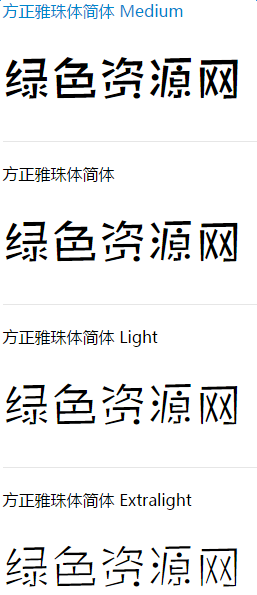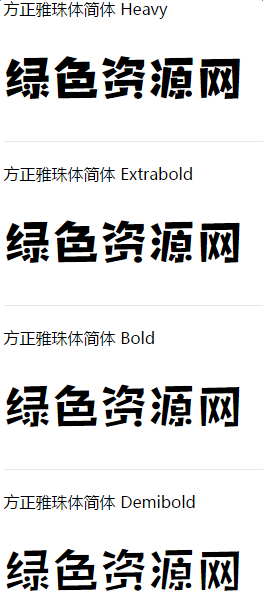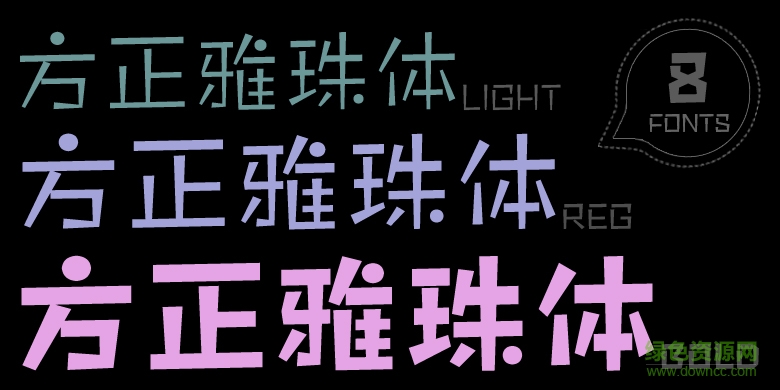
方正雅珠体是方正出品的字体,该字体粗细相间,钢劲有力,变化得当,深受广大文字书法爱好者喜欢,欢迎大家来本站踊跃下载哦!
方正雅珠体打破了传统字体的笔形和结构,将笔画以图形化的手法进行处理,且富于变化,横画处理成粗壮的矩形,竖划则近似于倒梯形,点、撇、捺、提也都处理成不规则的梯形,部分点画处理成椭圆形,整体给人以稚拙、欢快、跳脱、无拘无束、充满童趣的感觉,非常适合儿童相关的产品使用。